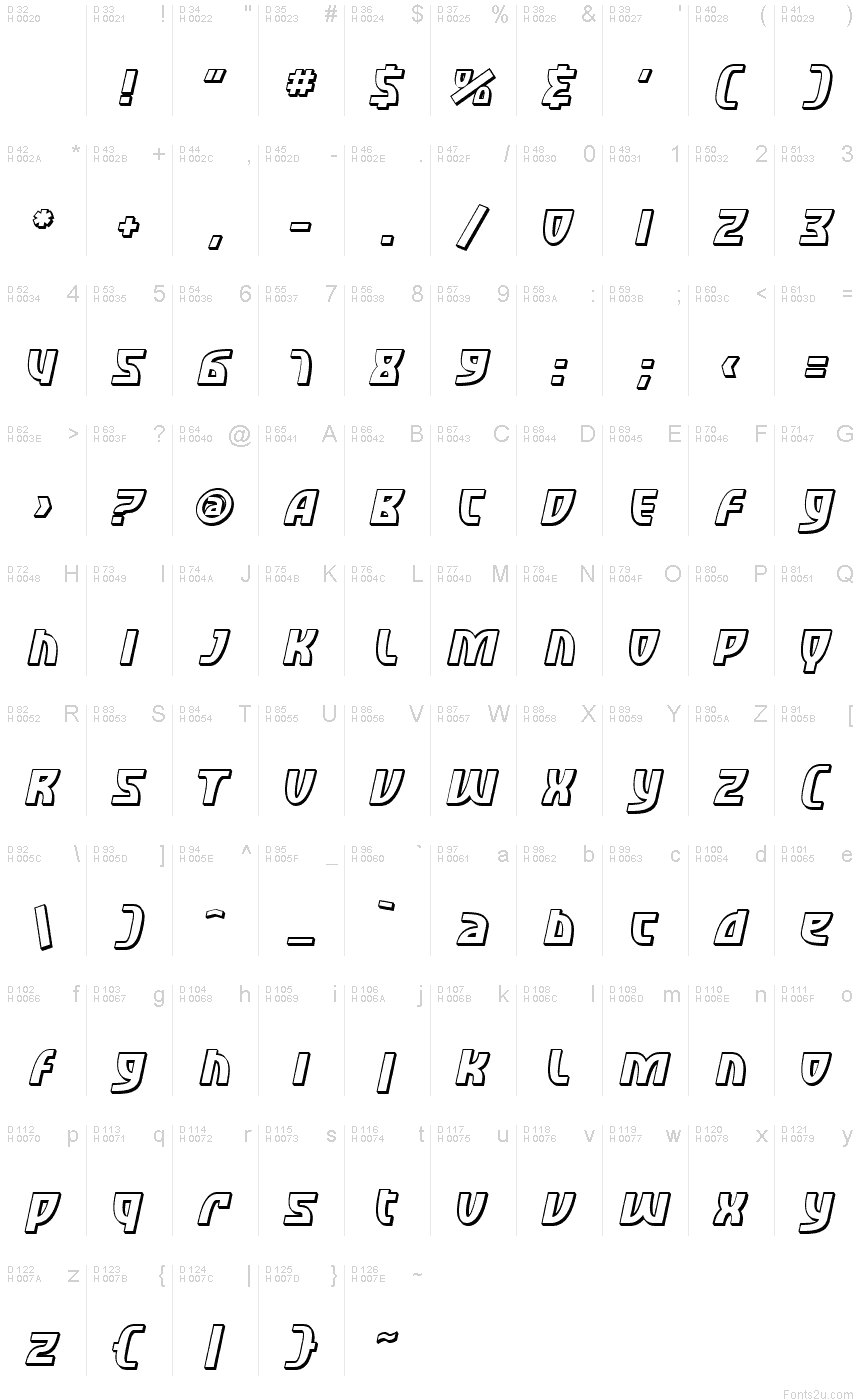
SF Retroesque Shaded Oblique
SF Retroesque Shaded Oblique von ShyFoundry ist eine kostenlose Retro-Display-Schrift mit markantem Vorwärtsdrang und klobigen Buchstabenformen im Arcade-Stil. Die Zeichen wirken wie aus kräftigen, geometrischen Blöcken gemeißelt, die durch die schräge Ausrichtung und einen scharfkantigen Schatten in Bewegung versetzt werden. Das verleiht der Schrift den lebendigen Flair der späten 70er Jahre und klassischer Videospiele.
Sie passt perfekt in Posterüberschriften, auf Albumcover, Verpackungen, Titelkarten und Logos, bei denen eine kostenlose Schrift sofortigen Retro-Charakter braucht, ohne überladen zu wirken. Da die Schattierung direkt in die Formen integriert ist und nicht nur als Dekoration dient, eignet sie sich auch hervorragend für kurze Cover-Texte und Badge-Grafiken, die Tiefe, Dynamik und einen verspielten Vintage-Touch verlangen.